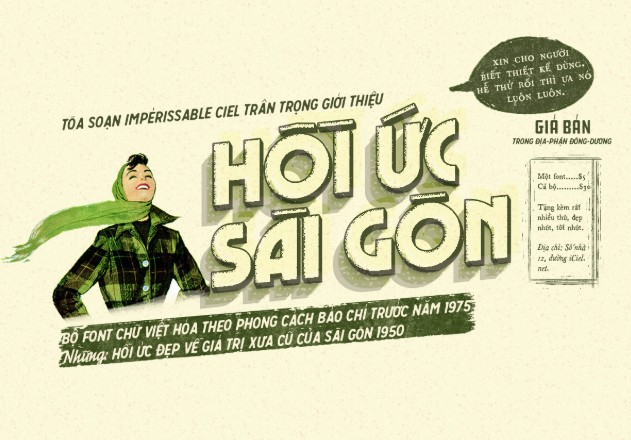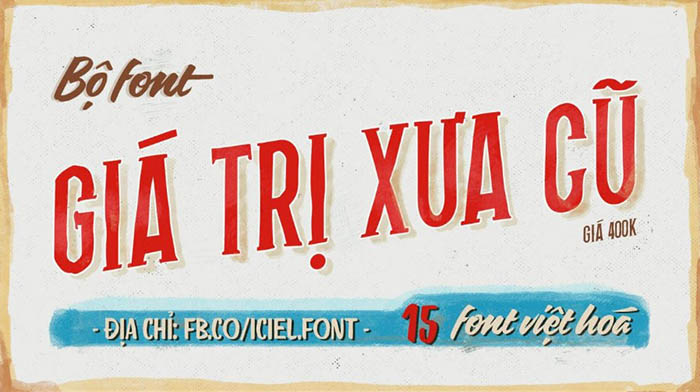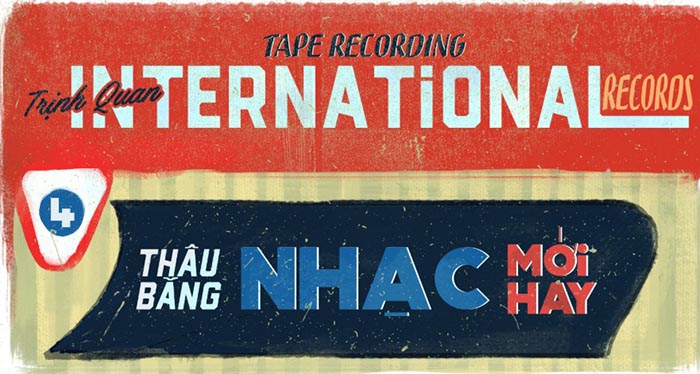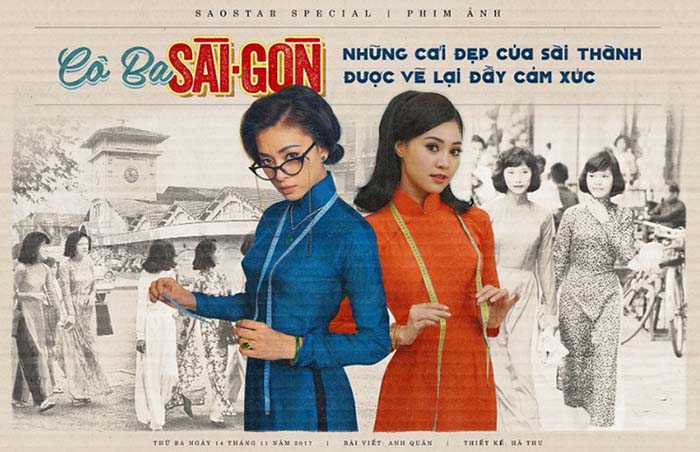
Tổng hợp 20 Font Retro cổ điển đẹp
Font Retro Việt hóa là lựa chọn lý tưởng cho những thiết kế mang hơi thở hoài cổ, như áp phích, pano, bìa sách hay các ấn phẩm truyền thông đậm chất xưa. Với phong cách retro đặc trưng gợi nhớ về hình ảnh Việt Nam những thập niên trước, các font chữ này không chỉ đẹp mắt mà còn gợi cảm xúc, giúp bạn tạo nên những thiết kế ấn tượng và đầy cảm hứng.
Font retro là font gì?
Font retro là kiểu chữ mang phong cách thiết kế gợi nhớ đến các thời kỳ trong quá khứ – thường là từ những năm 1950 đến 1980. Các font retro thường được lấy cảm hứng từ áp phích quảng cáo, bìa tạp chí, biển hiệu, truyền hình hoặc văn hóa đại chúng của các thập niên trước.
Tổng hợp các font retro đẹp hiện nay
Font retro việt hóa Hồi ức
Bộ font retro “Hồi ức Sài Gòn” của Iciel gồm 32 kiểu chữ Việt hóa độc đáo, được tuyển chọn và thiết kế dựa trên những tư liệu, hình ảnh quý giá về Sài Gòn trước năm 1975. Mỗi font chữ trong bộ sưu tập đều được tác giả trau chuốt tỉ mỉ đến từng chi tiết, từ hình dáng con chữ cho đến phong cách in ấn, nhằm tái hiện chân thực không khí xưa cũ trên báo chí, mẫu quảng cáo và bảng hiệu tại thành phố Sài Gòn những năm trước đổi mới. Bộ font không chỉ mang giá trị thẩm mỹ cao mà còn là một phần ký ức văn hóa thị giác – giúp người dùng cảm nhận được vẻ đẹp mộc mạc, hoài niệm và rất riêng của một thời đã qua.
Font chữ retro việt hóa giá trị xưa cũ
Bộ font “Giá Trị Xưa Cũ” của iCiel là một tác phẩm mang đậm hơi thở hoài niệm, lấy cảm hứng từ những bảng hiệu vẽ tay thời bao cấp – nơi nét chữ mộc mạc nhưng đầy cá tính từng là một phần quen thuộc trong đời sống đô thị Việt Nam.
Bộ font được thiết kế thủ công trong gần 2 tháng, với sự đầu tư kỹ lưỡng từ việc nghiên cứu phong cách bỏ dấu xưa cho đến việc trau chuốt từng nét vẽ. Font được Việt hóa tinh tế, mang phong cách rất riêng, vừa giữ được hồn cốt xưa cũ, vừa đảm bảo dễ đọc và ứng dụng cao. Với chất retro đặc trưng, “Giá Trị Xưa Cũ” là lựa chọn hoàn hảo cho các thiết kế poster, bảng biển quảng cáo, ấn phẩm truyền thông cần thể hiện không khí vintage, mộc mạc nhưng đầy cảm xúc.
Font chữ retro hòn ngọc viễn đông
“Hòn Ngọc Viễn Đông” là một sản phẩm đầy tâm huyết của iCiel, tái hiện tinh thần Sài Gòn xưa qua những kiểu chữ mang đậm dấu ấn thời đại. Lấy cảm hứng từ các bảng hiệu, logo cổ điển thế kỷ 19 – thời kỳ mà Sài Gòn được mệnh danh là “Hòn ngọc Viễn Đông” của châu Á – bộ font này là một hành trình trở về với vẻ đẹp hoài cổ và tinh tế.
Để tạo nên bộ font này, tác giả đã nghiên cứu hàng trăm bảng hiệu cũ của Sài Thành, tỉ mỉ chắt lọc từng chi tiết, thiết kế lại sao cho vừa thẩm mỹ vừa giữ nguyên hồn cốt của kiểu chữ cổ. Kết quả là một bộ sưu tập gồm 18 font chữ Việt hóa độc đáo, mang phong cách retro quý phái, sang trọng nhưng vẫn gần gũi và dễ ứng dụng. “Hòn Ngọc Viễn Đông” chắc chắn sẽ làm hài lòng cả những designer khó tính nhất – đặc biệt trong các dự án mang màu sắc hoài niệm, lịch sử, hay thiết kế mang đậm tinh thần Việt Nam xưa.
Font chữ retro Classique Saigon
Classique Saigon là một font chữ mang đậm dấu ấn hoài cổ, được thiết kế bởi Mạnh Nguyễn – một nhà thiết kế font trẻ đầy đam mê đến từ Hà Nội, người theo đuổi hành trình sáng tác những bộ chữ mang linh hồn Việt. Font này từng gây tiếng vang khi được sử dụng trong bộ phim điện ảnh nổi tiếng “Cô Ba Sài Gòn”. Từ đó, Classique Saigon không chỉ trở thành một hiện tượng trong cộng đồng thiết kế mà còn khơi dậy ký ức về một Sài Gòn hoa lệ, pha trộn giữa vẻ hiện đại và chất hồn quê Việt.